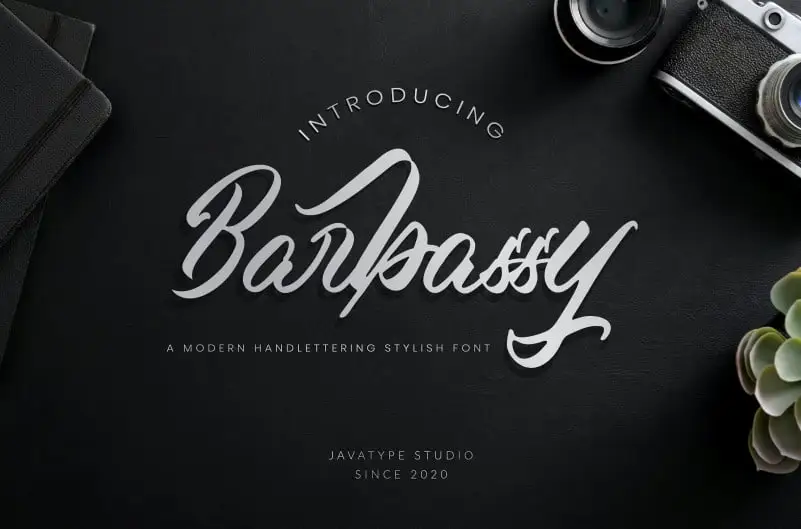
Barbassy Script Font – Download Grátis
A Barbassy Script Font é uma tipografia script com estilo de letra feito à mão usando pincel. Esta fonte abrange detalhes únicos e artísticos, resultado do trabalho direto do próprio punho usando um pen-pinchel. É perfeitamente adaptável para uso em headline, logotipo, roupas, convites, marcação, embalagem, anúncios etc. Suporta caracteres maiúsculos, minúsculos, pontuação, símbolos, números e alternativas. Esta fonte traz uma variedade de características, incluindo ligações, letras alternativas e suporte para múltiplos idiomas, fazendo-a um recurso versátil para qualquer projeto gráfico. Este é o tipo de font que você precisa quando quer dar vida a seu design através da personalização única e sofisticada.